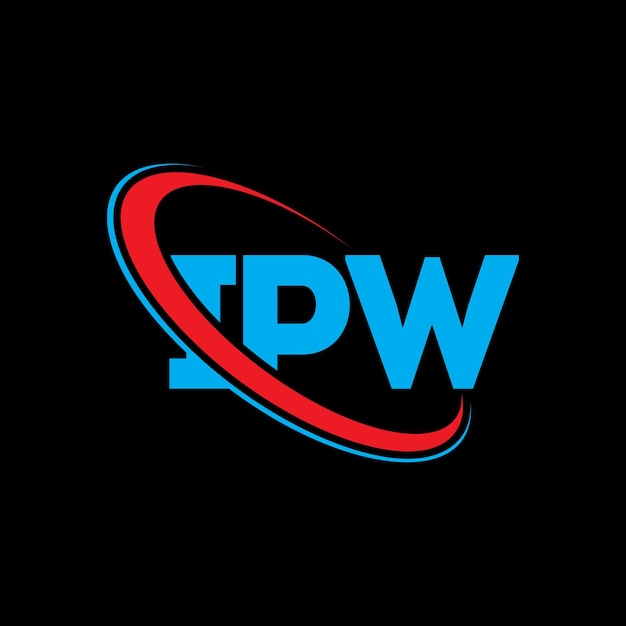
Logo TPW (litera TPW) - inicjały TPW (logo powiązane z okręgiem i dużymi literami) logo TPW (typografia TPW dla firmy technologicznej i marki nieruchomości)